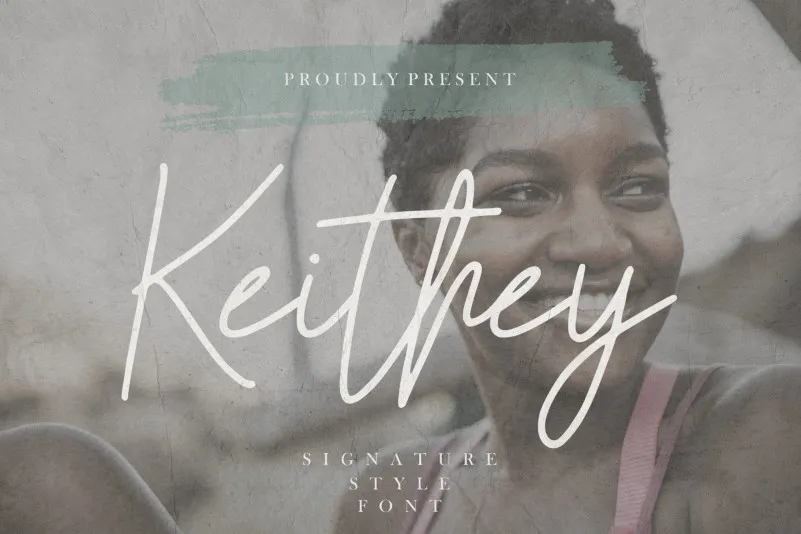
Keithey Font – Download Grátis
A fonte Keithey é perfeita para quem busca uma aparição elegante e autêntica em seus projetos digitais. Com um estilo de escrita manuscrita, ela traz um toque de naturalidade aos designs de embalagens de produto, marcações, revistas ou até mesmo a identificação das postagens nas redes sociais. A fonte é também perfeita para expressar palavras em atas de casamento, ou simplesmente usada como texto acima do fundo. Este é um estilo que vai muito além dos padrões tipográficos convencionais, oferecendo uma maneira única e sofisticada de destacar seu design. Seja para branding ou simplesmente personalizar o conteúdo em sua próxima criação visual, Keithey irá garantir um toque autêntico e único no projeto. Se você está procurando por mais opções de fontes, não hesite em explorar a vasta gama oferecida pelo Enigma Lettering Studio.